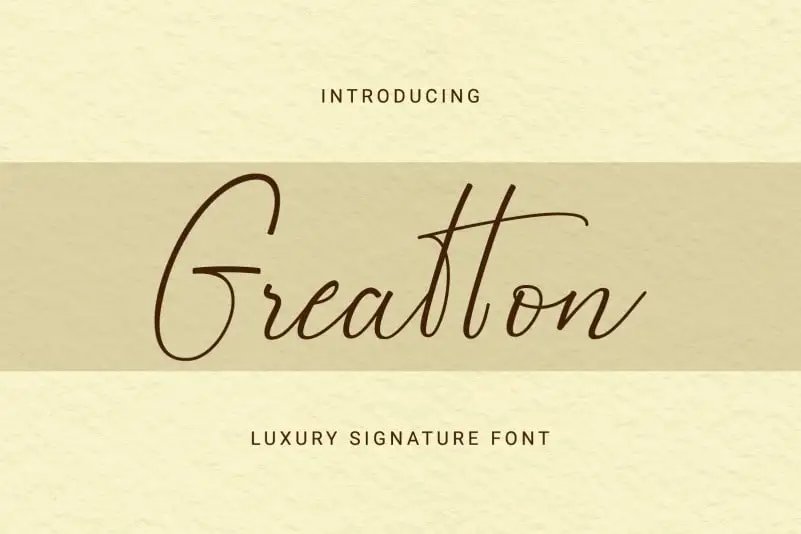
Greatton Script Font – Fonte Grátis
Greatton Script Font
A fonte Greatton Script é uma elegante fonte escrita a mão leve com um toque único e impactante. Suas linhas fluidas e traços delicados criam um visual refinado que se torna perfeito para adicionar um brilho luxuoso em qualquer projeto de design que você esteja criando. Esta fonte traz uma sensação especial à sua arte digital, tornando-a mais intrigante e memorável. Seja você criando cartazes publicitários, gráficos profissionais ou designs para revistas, a Greatton Script oferece um tom atraente que se destaca de outras fontes. Adicione vida ao seu trabalho com essa fonte única e encantadora.